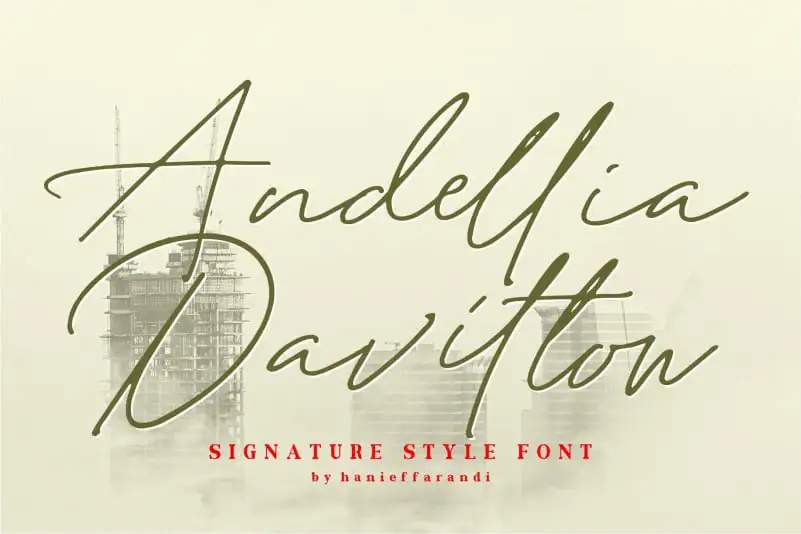
Andellia Davilton Handwritten Font – Download Grátis
Estamos muito felizes por você estar considerando a Andellia Davilton Handwritten Font para seu próximo projeto de design. Seja para criar uma assinatura poderosa para logomarca, marca na fotografia ou invitação de casamento, logo, etiquetas e revistas, esta fonte monoline script é perfeita. Andellia Davilton é um belo e único tipoface que combina elegância com originalidade. Criada pelo profissional Hanief Farandi, esta fonte é uma opção ideal para designers que buscam um estilo elegante e autêntico para seus projetos de design. Suas linhas curvas suaves e harmoniosas não apenas a tornam perfeita para assinaturas ou logomarcas, mas também a fazem ótima escolha para usar em etiquetas ou revistas que requerem um tom mais sofisticado. Seja você designer de moda, fotógrafo, designer gráfico ou editor de periódicos, Andellia Davilton Handwritten Font é uma fonte que pode enriquecer seu trabalho. Sem duvida, ela será a escolha perfeita para quem busca algo único e elegante para dar ao seu projeto um toque especial. Não hesite em experimentar esta fonte para sua próxima obra de arte gráfica!